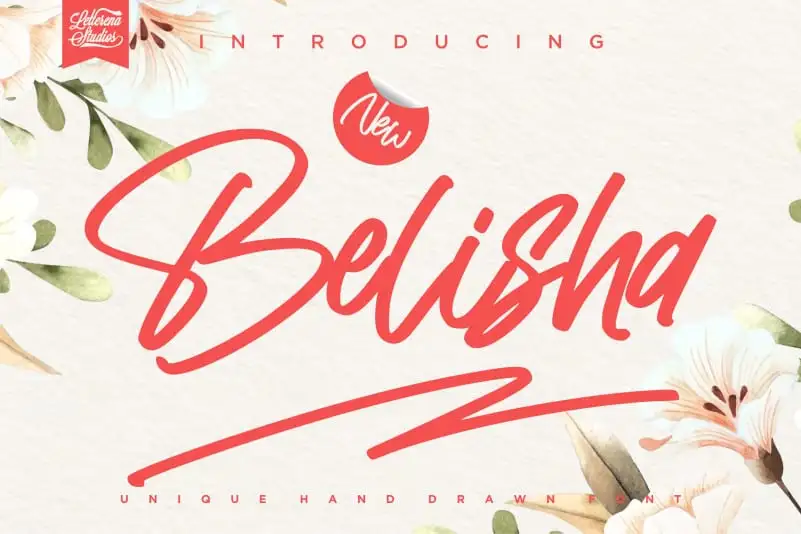
Belisha – Unique Handwritten Font – Download Grátis
A Belisha é uma fonte autografada única que traz um toque elegante à sua composição digital. Originária do trabalho meticuloso do designer letterenastudios, essa fonte vem de mãos apressadas carregando consigo traços distintivos e personalizados. Ideal para quem busca um acabamento cuidadosamente elaborado em seus projetos digitais, a Belisha é perfeita para aplicativos como contratos, cartões de visita ou até mesmo pequenos elementos gráficos para blogs pessoais. A fonte foi concebida com uma mão real, permitindo que você dê um toque personalizado ao seu design sem precisar recorrer a métodos digitais complicados. Como sua própria descrição sugere, esta fonte é destinada apenas para uso pessoal e não comerciais, mantendo-se fiel à natureza autêntica de cada letra. Seja você um estilista de moda ou um fotógrafo digital, a Belisha pode transformar seus designs digitais em algo verdadeiramente único e personalizado.